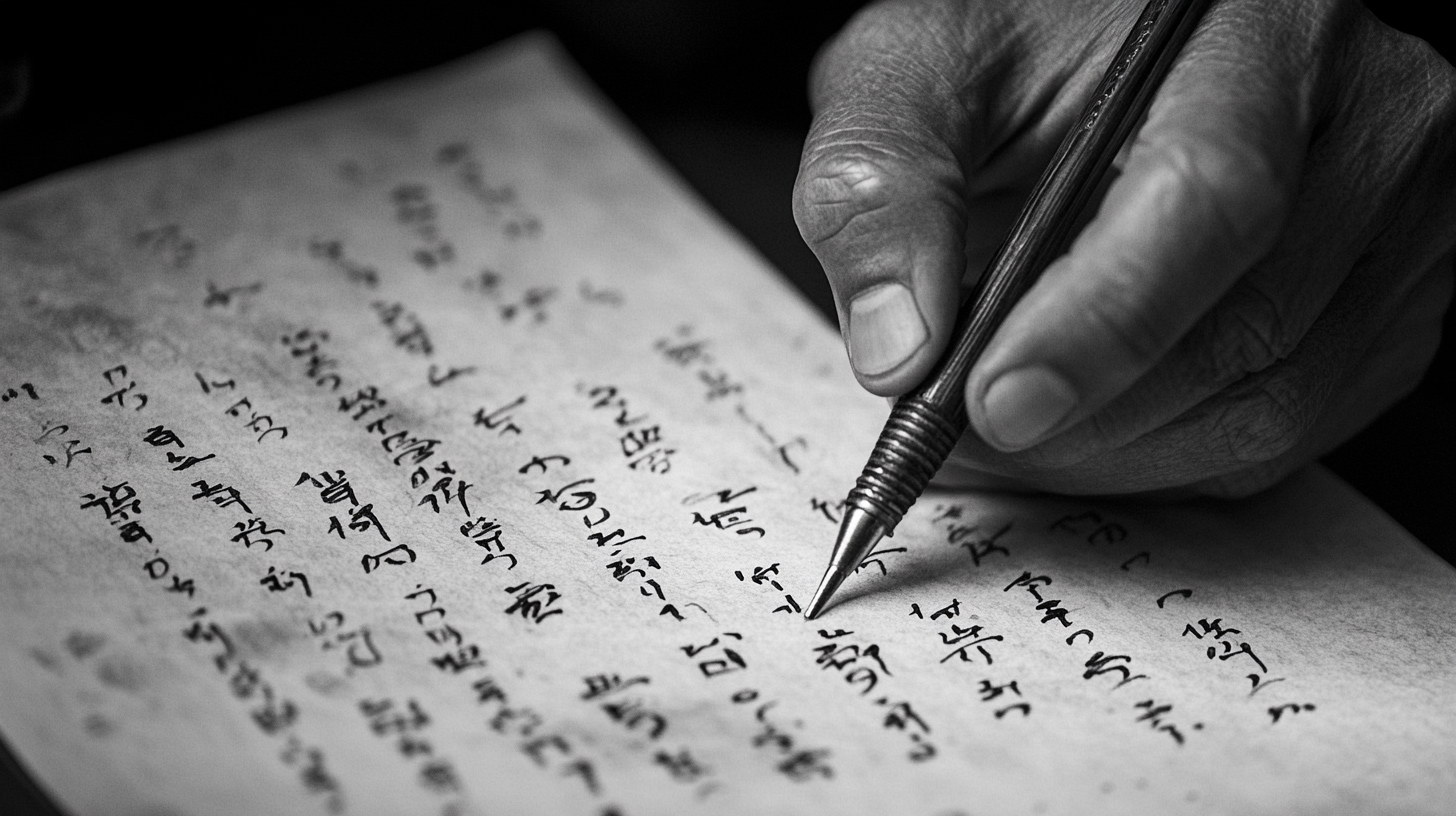
글씨 교정을 할 때 연필과 펜 중 어떤 것을 사용하는 것이 좋을까요? 🤔 어떤 필기구를 사용하느냐에 따라 획의 정확도와 필기 습관이 달라질 수 있어요! ✍
오늘은 연필과 펜의 장단점을 비교하고 상황별 추천 필기구를 알려드릴게요. 나에게 맞는 필기구를 선택하면 더 빠르고 효과적으로 글씨를 교정할 수 있어요! 🚀
🖊 글씨 교정할 때 필기구 선택이 중요한 이유
글씨 교정을 할 때 어떤 필기구를 사용하느냐가 매우 중요해요. 연필과 펜은 각각 다른 특성을 가지고 있어서 필기감, 획의 굵기, 필압 조절 능력 등에 영향을 줄 수 있어요! ✍
예를 들어, 연필은 필압을 조절하며 글씨를 교정하기 좋고, 펜은 일정한 획을 유지하는 연습에 유리해요. 각각의 장점을 잘 활용하면 더욱 효과적인 글씨 연습이 가능하답니다. 😊
📌 필기구 선택이 글씨 교정에 미치는 영향
요소 연필 사용 시 펜 사용 시 필기감 부드럽고 가벼움 매끄럽고 일정함 필압 조절 세밀한 조절 가능 획이 일정함 수정 가능 여부 쉽게 지울 수 있음 실수 시 수정 어려움 필기 속도 천천히 연습 가능 빠른 필기 연습 가능 이처럼 필기구 선택에 따라 글씨 교정 효과가 달라질 수 있어요. 그렇다면 연필을 사용할 때의 장점과 단점은 무엇일까요? 🤔
✏ 연필을 사용할 때의 장점과 단점
연필은 글씨 교정을 시작하는 분들에게 가장 추천하는 필기구 중 하나예요! 😊 획의 굵기를 자유롭게 조절할 수 있고, 실수했을 때 쉽게 수정할 수 있다는 장점이 있어요. ✍
하지만 연필도 단점이 있어요. 사용하는 연필의 종류나 필압에 따라 획이 일정하지 않거나, 너무 연하게 써질 수도 있답니다. 🤔
📌 연필을 사용할 때의 장점과 단점
구분 내용 ✅ 장점 필압 조절이 쉬워서 획 연습에 적합 ✅ 장점 잘못 써도 쉽게 지울 수 있어 부담이 적음 ✅ 장점 획을 부드럽게 연습할 수 있음 ❌ 단점 글씨가 연하게 써져서 흐릿해 보일 수 있음 ❌ 단점 심이 너무 부드러우면 글씨가 뭉개질 가능성 있음 ❌ 단점 자주 깎아야 해서 번거로울 수 있음 이처럼 연필은 초보자들에게 유용하지만 단점도 있기 때문에 필기 습관에 맞춰 사용하는 것이 좋아요! 😊 그렇다면 펜을 사용할 때는 어떤 장점과 단점이 있을까요? 🤔
🖊 펜을 사용할 때의 장점과 단점
펜은 연필과 달리 획이 일정하게 유지되기 때문에 글씨를 깔끔하게 교정하는 데 유리한 필기구예요. ✍ 특히 필기 속도를 높이고, 실전 필기 연습을 할 때 좋답니다! 😊
하지만 펜은 실수했을 때 수정이 어렵고, 획의 굵기를 자유롭게 조절하기 어렵다는 단점이 있어요. 그래서 처음 글씨를 교정할 때는 연필과 병행해서 사용하는 것이 더 효과적일 수 있어요! 🤔
📌 펜을 사용할 때의 장점과 단점
구분 내용 ✅ 장점 획이 일정해서 정리된 글씨체를 만들기 쉬움 ✅ 장점 필기 속도를 높이는 연습에 효과적 ✅ 장점 글씨가 선명하게 유지되어 가독성이 높음 ❌ 단점 실수하면 수정이 어려움 ❌ 단점 획의 굵기 조절이 어려워 자연스러운 필체 만들기 힘듦 ❌ 단점 오랫동안 사용하면 손에 부담이 갈 수 있음 펜은 글씨를 또렷하게 유지할 수 있지만 필압 조절이 어려워 초보자들에게는 부담이 될 수 있어요. 그렇다면 상황에 따라 어떤 필기구를 선택하는 것이 좋을까요? 🤔
🖋 상황별 추천 필기구
글씨 교정을 할 때 연필과 펜 중 어떤 걸 사용할지 고민된다면, 상황에 따라 적절한 필기구를 선택하는 것이 중요해요. 😊
예를 들어, 기본 획을 연습하는 단계에서는 연필이 좋고, 속도를 조절하며 실전 필기 연습을 할 때는 펜이 좋아요. 어떤 상황에서 어떤 필기구를 선택해야 할지 표로 정리해볼게요! ✍
📌 상황에 따른 최적의 필기구 선택
상황 추천 필기구 이유 기본 획 연습 ✏ 2B 연필 필압을 조절하며 정확한 획 연습 가능 글씨 크기 & 균형 잡기 ✏ 모눈 노트 + 연필 일정한 크기와 간격을 유지하기 쉬움 속도 조절 연습 🖊 유성 볼펜 부드럽게 써지면서 일정한 속도를 유지 가능 실전 필기 연습 🖋 만년필 획의 흐름을 자연스럽게 연습할 수 있음 시험, 필기용 🖊 중성 펜 선명하게 써지면서 손이 덜 피로함 각 상황에 맞는 필기구를 사용하면 훨씬 효율적으로 글씨를 교정할 수 있어요! 😊 그렇다면 연필과 펜을 함께 사용하는 방법도 있을까요? 🤔
✍ 연필과 펜을 함께 사용하는 방법
연필과 펜은 각각 장점이 다르기 때문에 함께 사용하면 글씨 교정 효과를 극대화할 수 있어요! 😊 연필로 기본 획과 글자 크기를 연습한 후, 펜으로 실전 필기를 연습하는 방식이 효과적이에요. ✏🖊
많은 명필들도 처음에는 연필을 사용해 획을 정리한 후, 펜으로 완성도를 높이는 연습을 했어요. 이제 연필과 펜을 효과적으로 병행하는 방법을 알아볼까요? 🤔
📌 연필과 펜을 함께 활용하는 방법
단계 사용 필기구 설명 1단계 ✏ 연필 기본 획과 글씨 크기 연습 (모눈 종이 활용) 2단계 ✏ 연필 자주 쓰는 단어 및 짧은 문장 연습 3단계 🖊 펜 연필로 쓴 글씨를 덧대어 필기감 익히기 4단계 🖊 펜 실전 필기 연습 (노트 필기, 필사 등) 이처럼 연필과 펜을 번갈아 가며 사용하면 필압 조절 능력을 키우고, 더 정돈된 글씨체를 완성할 수 있어요! 😊 그렇다면 나에게 가장 잘 맞는 필기구는 어떻게 선택할 수 있을까요? 🤔
🧐 나에게 맞는 필기구 선택법
글씨 교정에 성공하려면 자신에게 가장 잘 맞는 필기구를 선택하는 것이 중요해요! ✍ 사람마다 필기 습관과 손의 힘이 다르기 때문에 연필이 더 편한 사람도 있고, 펜이 더 잘 맞는 사람도 있어요. 😊
그렇다면 어떤 기준으로 필기구를 선택하면 좋을까요? 아래 표를 참고해서 나에게 맞는 필기구를 찾아보세요! 🔍
📌 필기 습관별 추천 필기구
필기 스타일 추천 필기구 이유 손에 힘을 많이 주는 편 ✏ 2B 연필 필압 조절이 쉽고 손의 피로를 줄여줌 획이 자주 흔들리는 편 🖊 유성 볼펜 획이 깔끔하게 유지됨 필기 속도가 너무 느린 편 🖋 만년필 부드럽게 써지고 필기 속도를 조절하기 쉬움 시험이나 노트 필기가 많은 경우 🖊 중성 펜 잉크 번짐이 적고 장시간 필기에 적합 나의 필기 습관을 고려해서 가장 적합한 필기구를 선택하면 더 편안하고 효과적으로 글씨 교정을 할 수 있어요! 😊 이제 필기구 선택과 글씨 교정에 대한 자주 묻는 질문들을 정리해볼까요? 🤔
Q1. 글씨 교정 초보자는 연필과 펜 중 어떤 걸 먼저 사용해야 하나요?
A1. 초보자는 연필로 기본 획 연습부터 시작하는 것이 좋아요. 연필은 필압 조절이 쉽고, 실수했을 때 쉽게 지울 수 있어 처음 글씨 교정을 할 때 부담이 적어요. ✏
Q2. 연필을 사용하면 손에 힘이 많이 들어가는데 어떻게 해야 하나요?
A2. 연필을 너무 꽉 쥐지 말고, 손가락과 손목을 부드럽게 유지하는 것이 중요해요. 그립 보조 연필을 사용하면 자연스러운 필기 습관을 기를 수 있어요. 😊
Q3. 펜을 사용할 때 획이 너무 두꺼워지는데 해결 방법이 있나요?
A3. 필기구의 잉크 흐름이 원활한 0.5mm 이하의 얇은 펜을 사용해보세요. 또한, 필압을 줄이고 손목을 가볍게 움직이면 획이 더 깔끔해질 수 있어요! 🖊
Q4. 만년필은 글씨 교정에 적합한가요?
A4. 네, 만년필은 부드럽게 써지면서 획의 흐름을 자연스럽게 만드는 데 도움을 줘요. 하지만 초보자보다는 기본 필기 습관이 잡힌 후 사용하는 것이 좋아요. 🖋
Q5. 시험 필기할 때 어떤 펜이 가장 좋을까요?
A5. 중성 펜(0.5~0.7mm)을 추천해요. 필기감이 부드럽고 손이 덜 피로해서 장시간 필기할 때 효과적이에요. 📝
Q6. 글씨 교정을 위해 연필과 펜을 함께 써도 괜찮나요?
A6. 네! 연필로 기본 연습을 하고, 펜으로 실전 필기를 연습하는 방식이 효과적이에요. 이렇게 하면 획의 안정성과 필기 속도를 동시에 향상시킬 수 있어요! 😊
Q7. 필기구 선택이 글씨체에 큰 영향을 주나요?
A7. 네, 필기구에 따라 필압 조절, 획의 선명도, 필기 속도가 달라지기 때문에 자신에게 맞는 필기구를 선택하는 것이 중요해요! ✨
Q8. 글씨 교정을 위한 최고의 필기구는 무엇인가요?
A8. 정답은 없지만, 초보자는 2B 연필로 기본 연습을 하고, 필기 속도와 실전 연습이 필요할 때는 유성 볼펜을 사용하는 것이 좋아요. 본인에게 맞는 필기구를 찾는 것이 가장 중요해요! ✍
이제 연필과 펜 중 어떤 필기구를 선택해야 할지 감이 오셨나요? 😊 자신에게 맞는 필기구를 찾아 꾸준히 연습해보세요! ✨